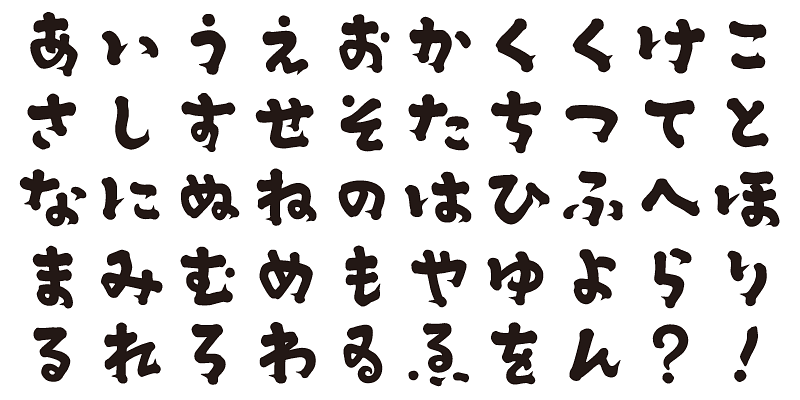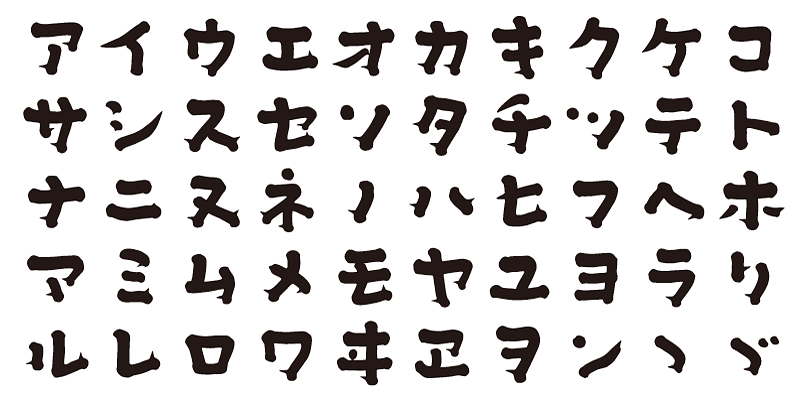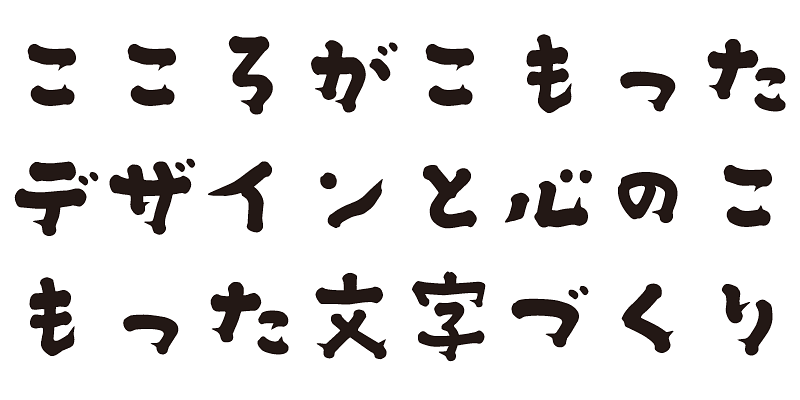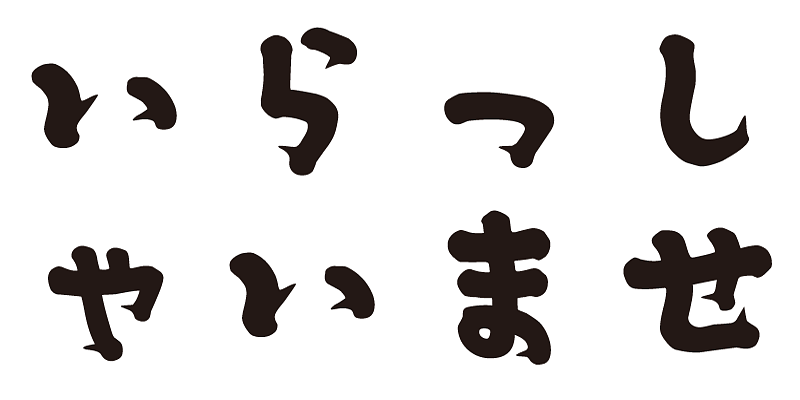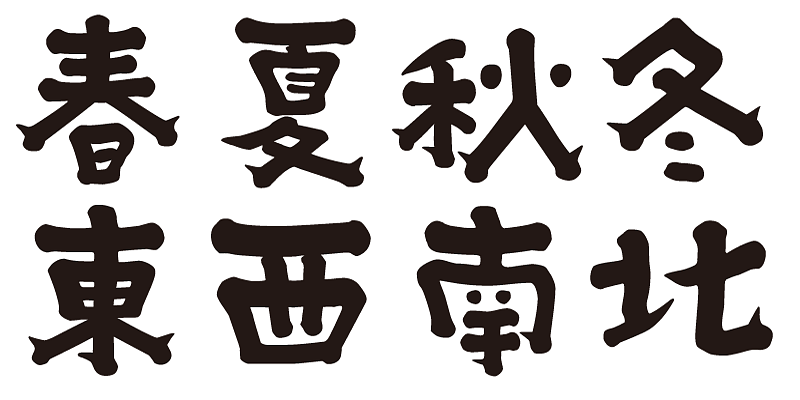
Como un caballero alegre y elegante caminando por una zona antigua de Tokio, este tipo de letra tiene una naturaleza dinámica con una fuerte formación de trazos.
Todas las fuentes de esta familia tipográfica contienen 1000 caracteres kanji, además de hiragana, katakana, caracteres alfanuméricos y signos de puntuación.